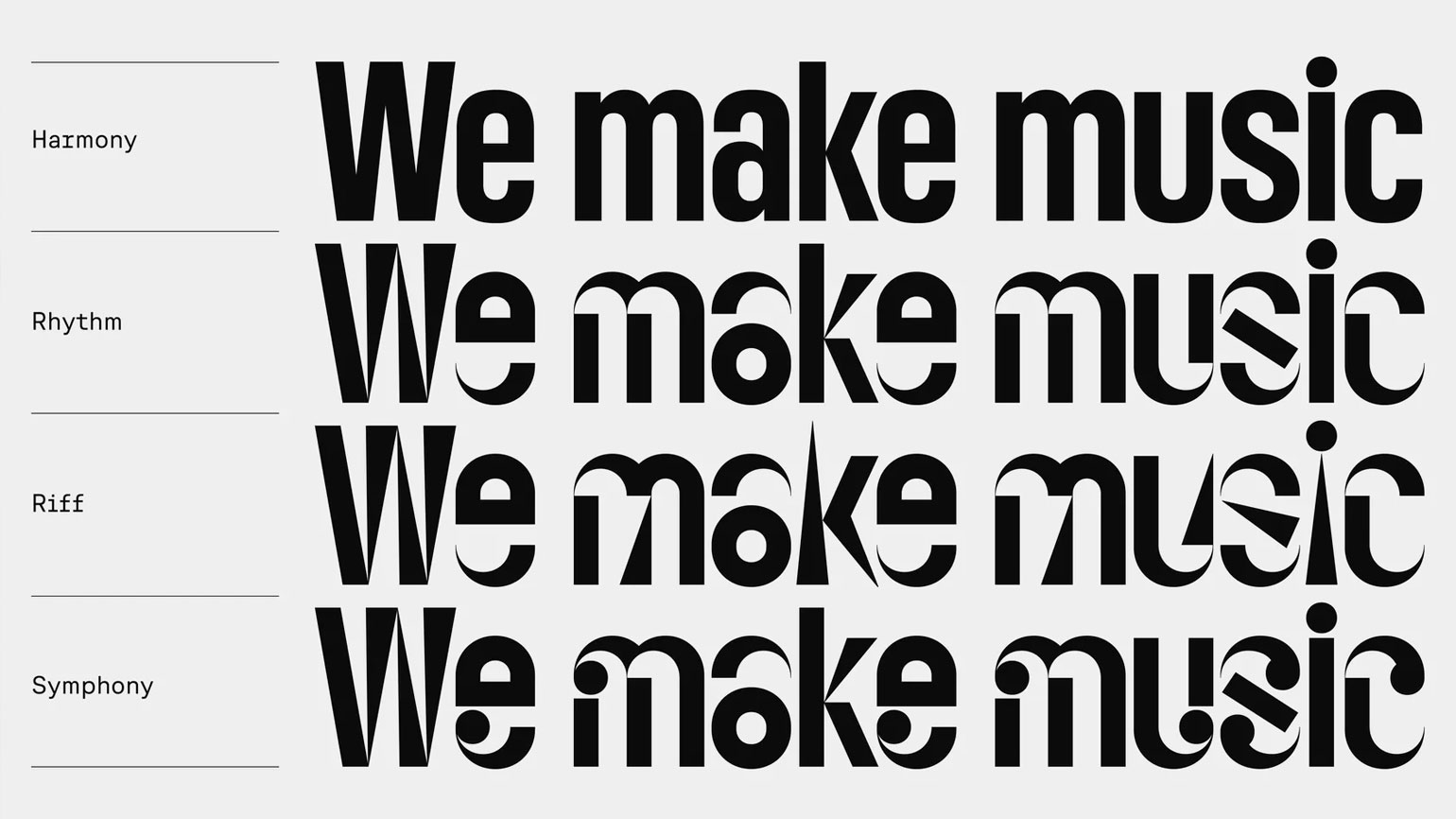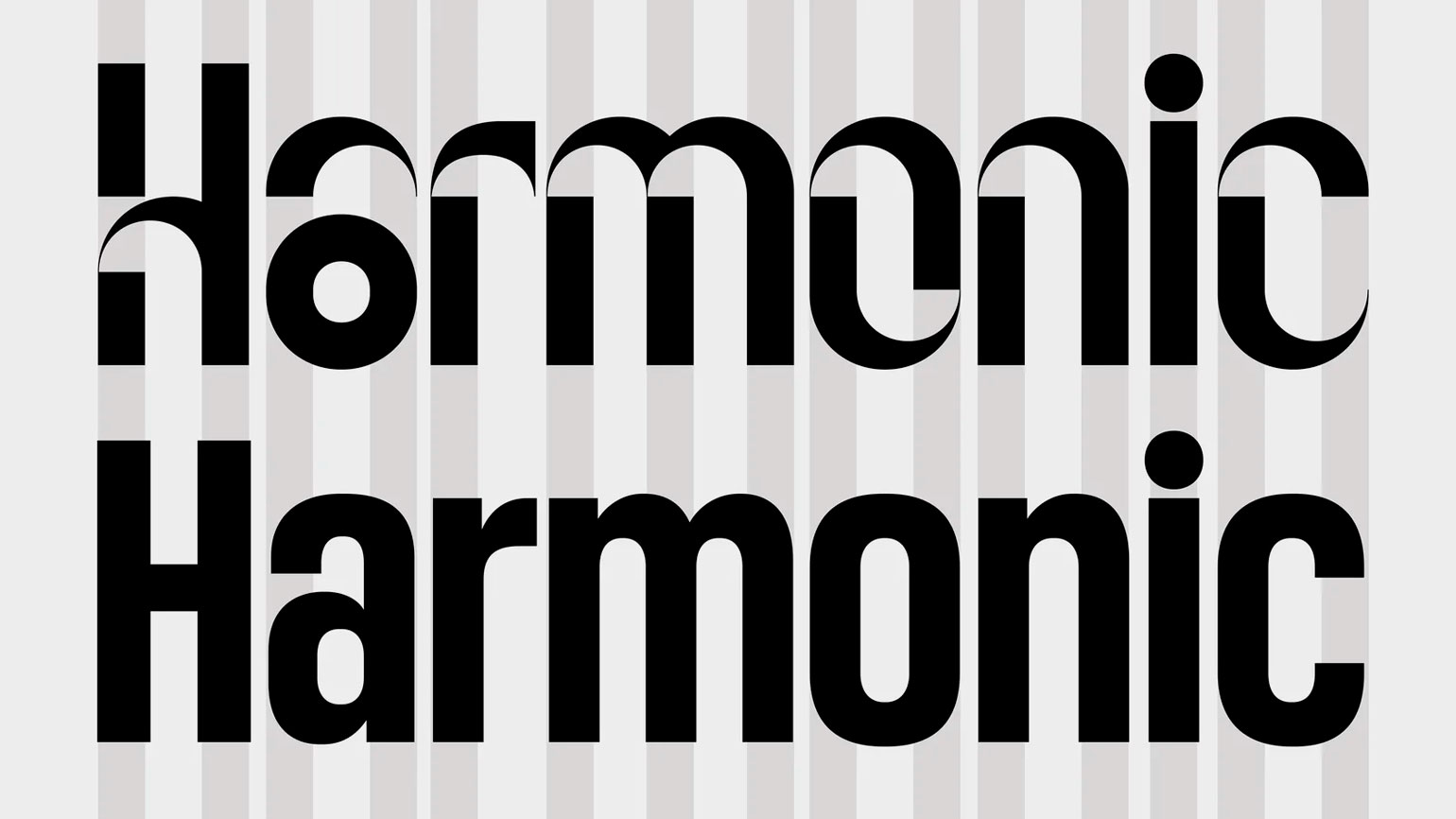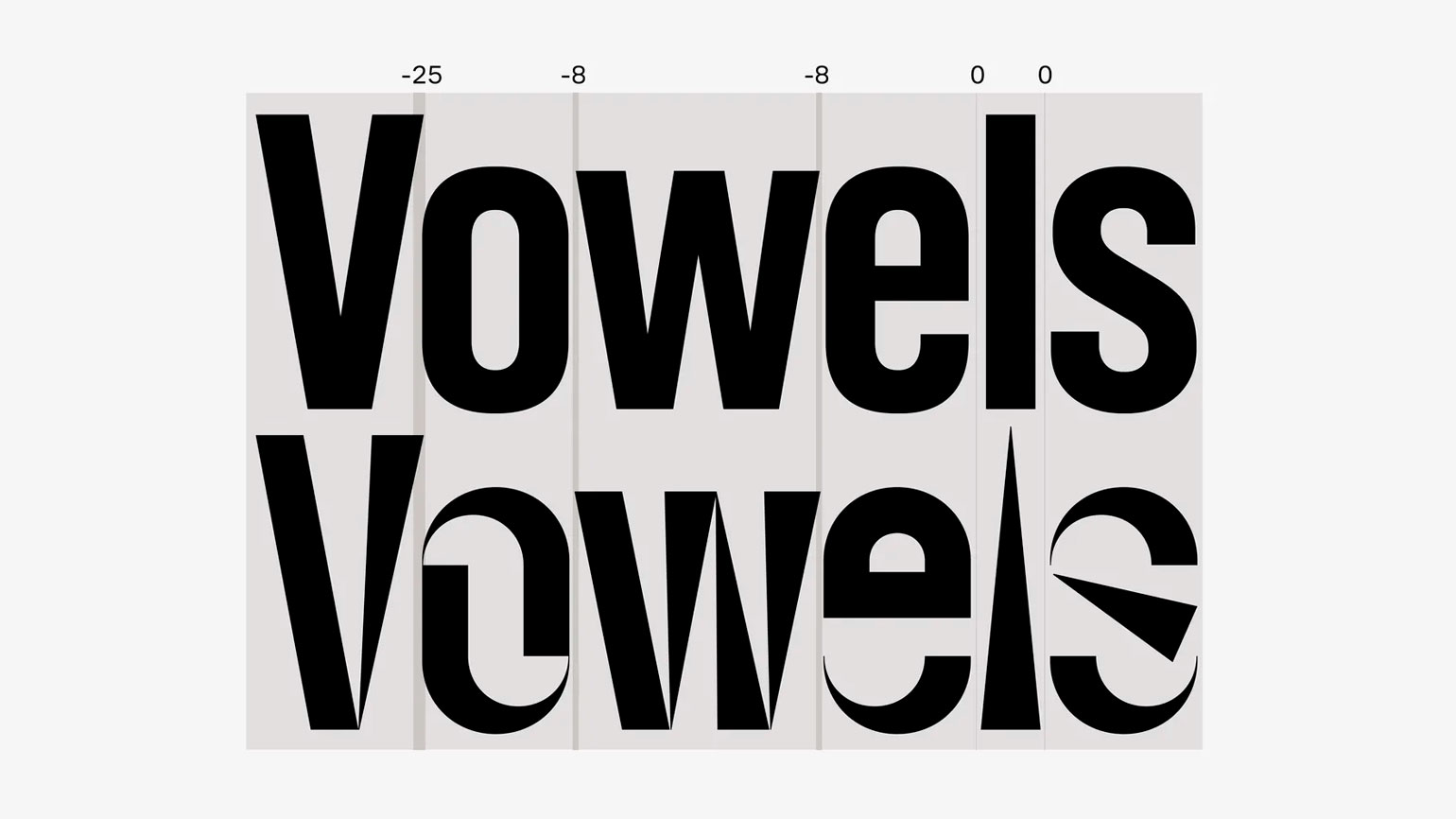
Contrast Foundry разработала шрифт для Muse Group
Это кипрская IT-компания, создавшая приложения Ultimate Guitar, MuseScore и MuseClass.
Аудитория платформ превышает 400 миллионов человек, но до недавнего времени у бренда не было единой айдентики. За разработку новой системы отвечали студия Collins и шрифтовая команда Contrast Foundry.
В основу креативной концепции легла идея творческого полёта. Дизайнер Инджила Самад Али предложила создать шрифт, который передаёт ритм и характер бренда через модули, вдохновлённые нотной записью. Совместно с Ребекой Арсе и Ником Эйсом она сформировала креативное направление, а Contrast Foundry воплотила идею в типографическую систему.
Так появились модульные гарнитуры Muse Display — Rhythm, Riff и Symphony — каждая со своей пластикой, а ещё базовое начертание Muse Display Harmony, адаптированное на основе шрифта CoFo Kak Medium. Особенность системы — дуплексность: буквы в разных начертаниях имеют одинаковую ширину, чтобы можно было плавно менять стиль текста, не меняя длину строки.
Работа над системой потребовала ряда отступлений от строгих правил. Например, дизайнеры увеличили высоту строчных знаков ради читаемости и мягко перерисовали формы CoFo Kak, чтобы сблизить его характер с модульными шрифтами. Были созданы альтернативные символы, расширены наборы модулей и переработана логика построения некоторых букв и цифр.
Параллельно команда обновила иконки продуктов Muse Group: их формы стали опираться на шрифт, но рисунок сделали более удобным для экранов и мелких размеров.